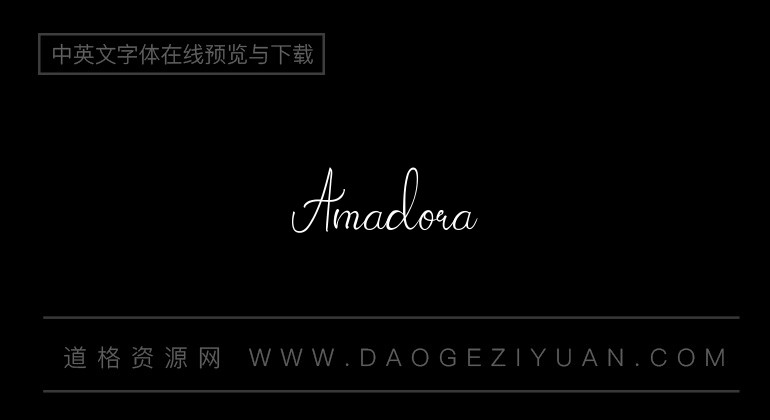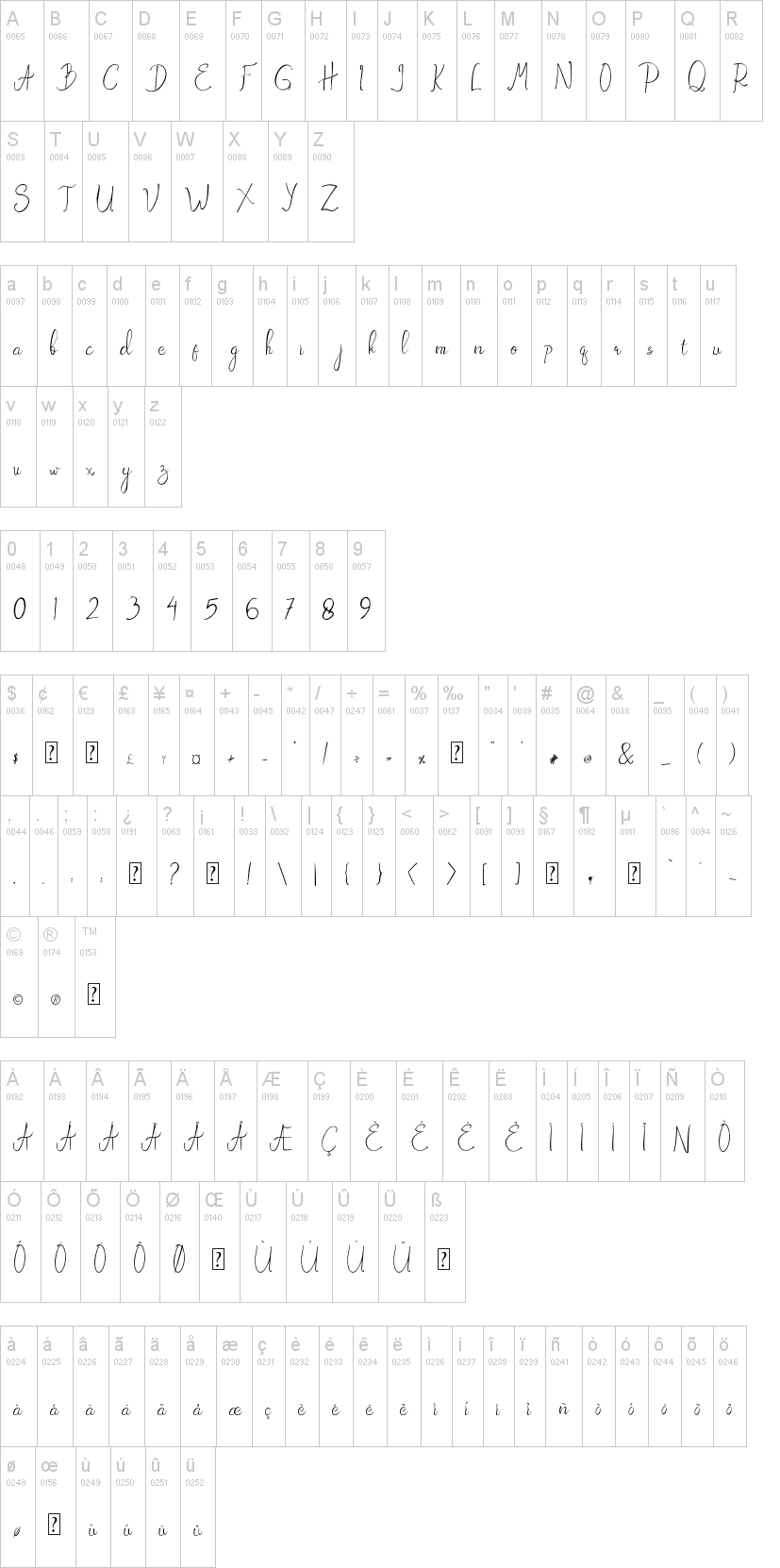
Amadora 是一款源自葡萄牙的脚本字体,由葡萄牙设计师 Ricardo Santos 于 2017 年设计。它具有柔和、温暖的线条,适合用于浪漫的文字排版。Amadora 的特点是拥有优美的曲线,字母间的间距也比较大,使其看起来更加清晰明了。它有多种重量,包括常规、粗体、细体等。Amadora 字体适合用于浪漫的文字排版,比如婚礼邀请函、浪漫的封面、浪漫的书籍封面等等。内容介绍
Amadora是一款非常不错的手写艺术字体,具有很好的视觉感,适合于文化类的宣传设计、商业类品牌的广告和产品包装设计以及个性化文字排版等较多场景。